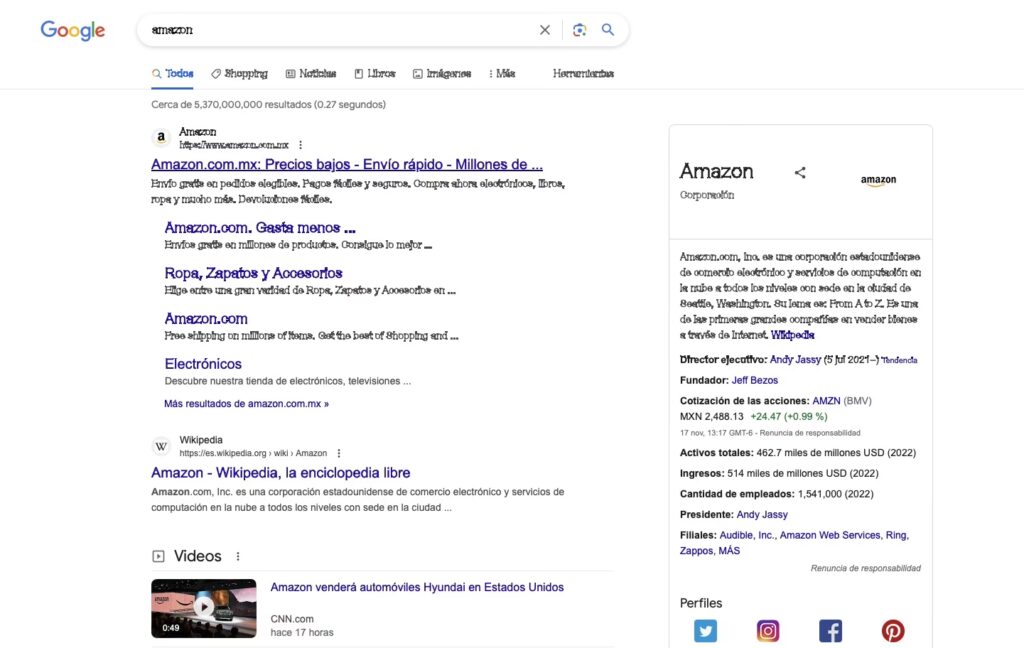
I en verden, hvor mobiltelefoner er vores primære adgang til internettet, er en hurtig og visuelt tiltalende brugeroplevelse afgørende. En stor del af denne oplevelse handler om typografi – hvordan tekst vises på skærmen. Google Fonts er blevet en uundværlig ressource for webudviklere, der ønsker at pifte deres sider op med unikke og gratis skrifttyper. Men selvom de er nemme at implementere, kan der opstå uventede udfordringer, især når det kommer til ydeevne og skrifttypens udseende på forskellige enheder, herunder din iPhone eller Android-telefon. Denne artikel dykker ned i de mest almindelige problemer og tilbyder løsninger, der sikrer, at dine websider ser skarpe ud og indlæses lynhurtigt, uanset hvor brugeren befinder sig.
Fra takkede bogstaver, når du forsøger at hoste skrifttyperne selv, til mystiske indlæsningsproblemer på specifikke mobile browsere som Chrome på iOS, er der mange faldgruber. Vi vil udforske årsagerne bag disse problemer og give dig de nødvendige værktøjer og viden til at optimere dine webskrifttyper for den bedst mulige mobiloplevelse. Målet er at give dig en dybere forståelse af, hvordan skrifttyper fungerer på nettet, og hvordan du kan udnytte Google Fonts' fulde potentiale uden at kompromittere ydeevnen.
Hvorfor ser dine lokalt hostede skrifttyper takkede ud?
Mange webudviklere vælger at downloade Google Fonts og hoste dem direkte på deres egen server. Dette gøres ofte i et forsøg på at forbedre ydeevnen eller for at have mere kontrol. Men til stor frustration opdager man ofte, at de lokalt hostede skrifttyper ser markant grovere, mere takkede og mindre glatte ud sammenlignet med, når de indlæses direkte fra Google Fonts' CDN (Content Delivery Network). Hvad er årsagen til dette?
Svaret ligger i noget, der kaldes skrifttypeantydning (font hinting) og den måde, operativsystemer (som Windows, macOS, iOS) og browsere (som Chrome, Safari) render teksten på. Skrifttypeantydning er ekstra instruktioner indlejret i skrifttypefilen, der hjælper med at justere bogstavernes form og placering, så de ser skarpe og læselige ud, især på lavopløselige skærme eller ved små skriftstørrelser. Windows, især ældre versioner som XP, bruger i høj grad skrifttypeantydning til at forbedre tekstgengivelsen. Hvis ClearType (Windows' underpixel-gengivelsesteknologi) er slået fra, som det er tilfældet for nogle brugere, bliver skrifttypeantydning endnu mere kritisk for at undgå takkede kanter.
Google Fonts' CDN er utroligt intelligent. Når din browser anmoder om en skrifttype fra Google, analyserer Google din browsers brugeragentstreng (som afslører operativsystem og browser). Baseret på dette leverer Google en optimeret version af skrifttypen. For Windows-brugere sendes skrifttypefiler, der indeholder hinting-instruktioner. For macOS- og iOS-brugere, som ikke bruger hinting på samme måde (de stoler mere på høj skærmopløsning og anti-aliasing), leveres der ofte mindre filer uden disse hinting-instruktioner. Når du downloader en skrifttype manuelt, får du typisk en generisk version, som måske ikke indeholder den optimale hinting for alle platforme, eller den kan indeholde hinting, der er unødvendig og gør filen større for nogle brugere.
En anden faktor er skrifttypedelætning (font subsetting). Google Fonts leverer kun de tegnsæt, der er nødvendige for det sprog, websiden bruges til (f.eks. kun latinske tegn, hvis det er engelsk eller dansk). Dette reducerer filstørrelsen markant. Når du downloader en skrifttype via tredjepartsværktøjer, får du muligvis hele skrifttypen med alle tegnsæt, hvilket resulterer i en meget større fil. Større filer betyder længere indlæsningstider, hvilket er særligt mærkbart for mobilbrugere på langsommere netværksforbindelser. Den øgede filstørrelse kan også bidrage til opfattelsen af, at skrifttypen er 'grovere', da browseren skal behandle mere data.
Google Fonts vs. Selv-hosting: En Kamp om Ydeevne
Valget mellem at bruge Google Fonts' CDN direkte eller at selv-hoste skrifttyperne er en afvejning mellem bekvemmelighed, ydeevne og kontrol. Begge tilgange har deres fordele og ulemper, især når man tager mobil ydeevne i betragtning.
Google Fonts CDN's Fordele og Ulemper
Den primære fordel ved at bruge Google Fonts direkte er den utrolige bekvemmelighed og automatiske optimering. Google håndterer alt: global distribution via deres CDN, automatisk identifikation af browser og operativsystem for at levere den mest optimerede skrifttypefil (f.eks. WOFF2 for moderne browsere, WOFF for ældre), skrifttypedelætning og den korrekte CSS med @font-face regler. Dette betyder minimal opsætning for udvikleren.
Men der er også ulemper. En stor ulempe er de ekstra forbindelsesomkostninger. Når du inkluderer en Google Font, sker der typisk to separate HTTP-anmodninger: først til fonts.googleapis.com for CSS-filen, og derefter til fonts.gstatic.com for de faktiske skrifttypefiler. Hver af disse anmodninger kræver tid til DNS-opslag, TLS-håndtryk og selve dataoverførslen. På mobile netværk, hvor latens er højere, kan disse ekstra forbindelser forlænge den samlede indlæsningstid betydeligt.
Desuden er den traditionelle måde at inkludere Google Fonts på (via et <link rel="stylesheet"> tag i HTML's <head>) render-blocking. Det betyder, at browseren stopper med at rendere resten af siden, indtil CSS-filen (og dermed også skrifttypefilerne) er downloadet og behandlet. Dette kan føre til en forsinket “first paint” og “first contentful paint”, hvilket giver en oplevelse af en langsom webside, især på mobiltelefoner med dårlig dækning.
&display=swapi din Google Fonts URL for at undgå usynlig tekst. - Vælg kun de nødvendige skrifttypevægte og -stile.
- Angiv altid fallback-skrifttyper i din CSS.
- Overvej selv-hosting og brug WOFF2-formatet samt
<link rel="preload">for kritiske skrifttyper. - Sørg for, at dine selv-hostede skrifttypefiler er korrekt subsetted og hintede (hvis nødvendigt for din målgruppe).